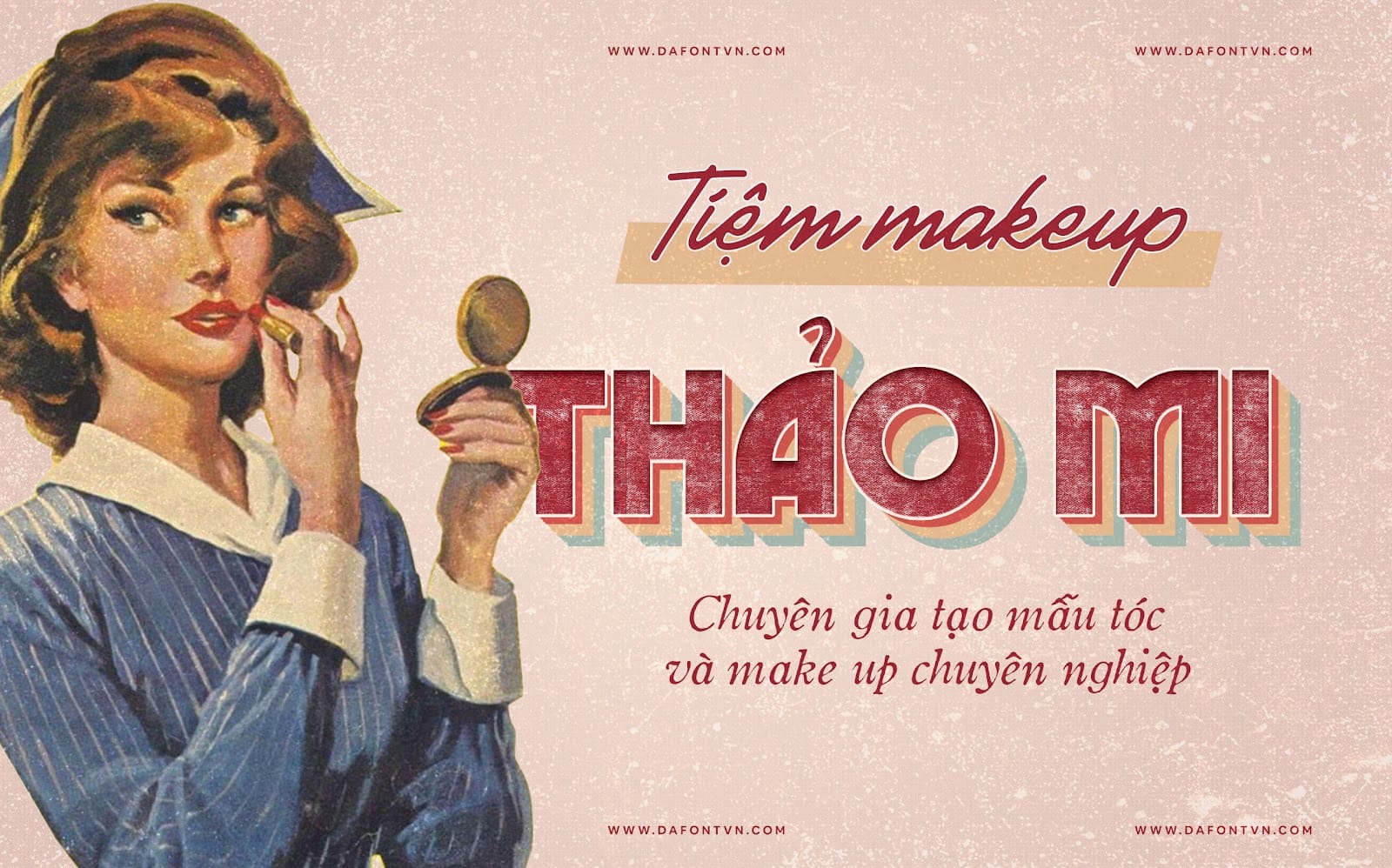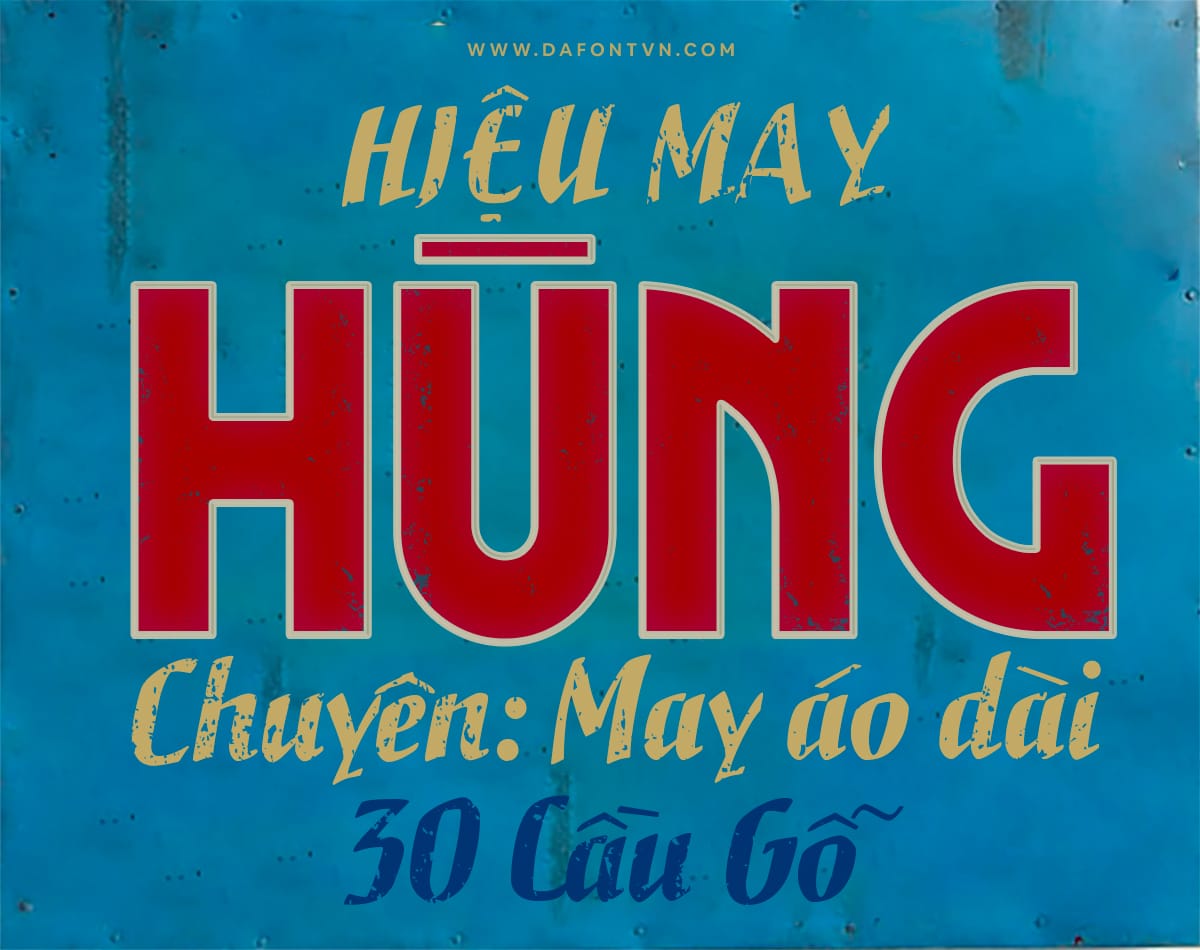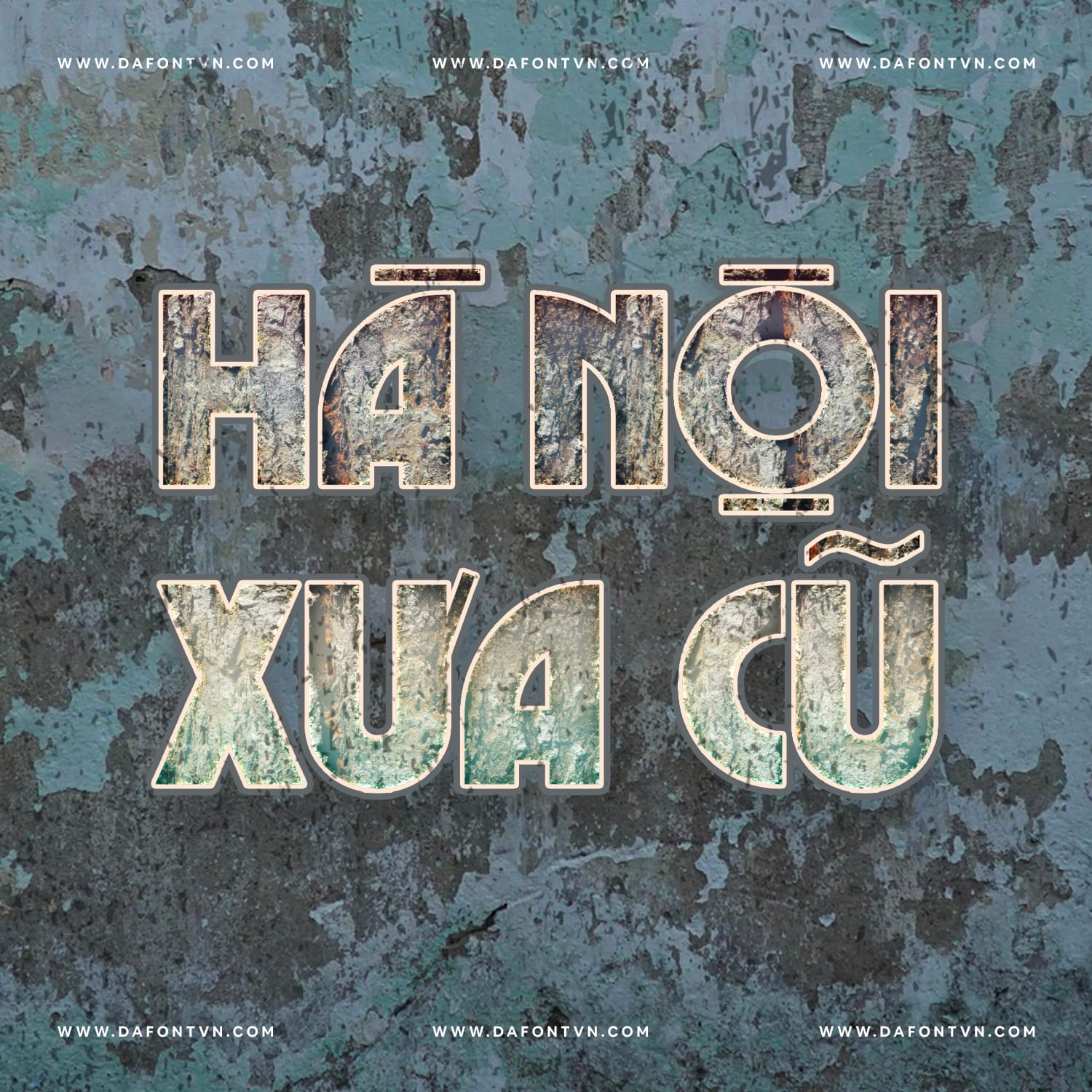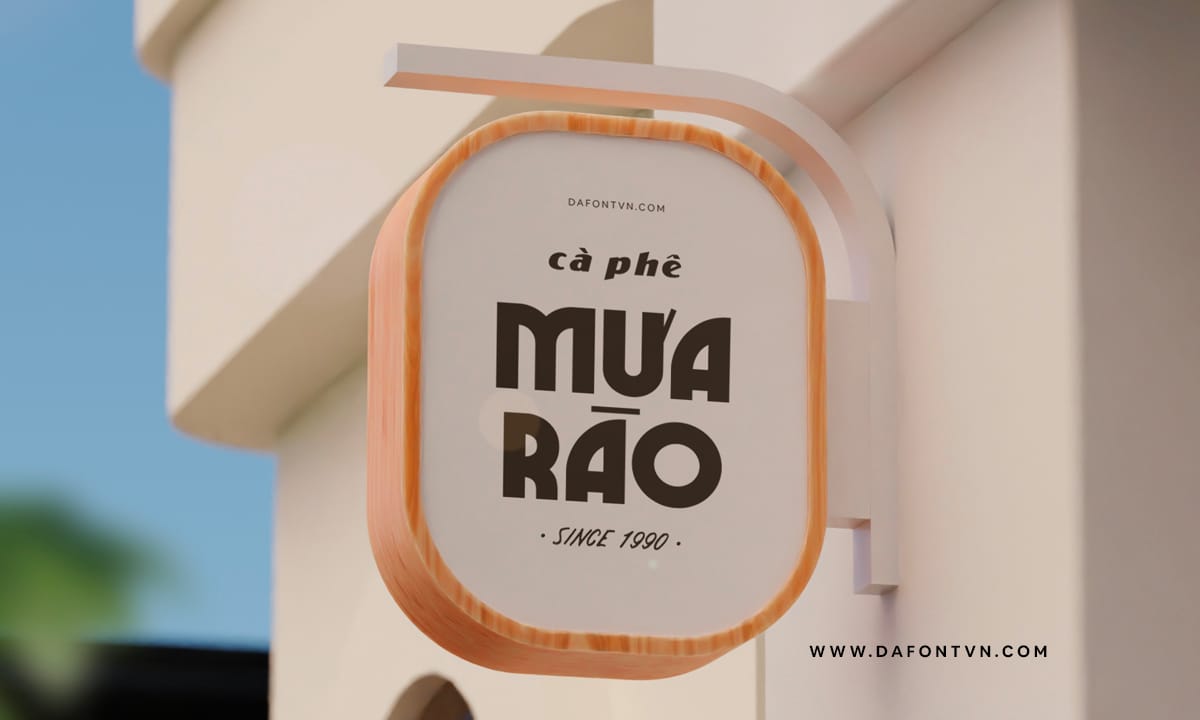
iCielBC Lodestone là một kiểu chữ sans serif ra đời vào năm 2017. Thiết kế ban đầu của nó có tên là “Marvin” và được tạo bởi Face Photosetting (London) vào đầu những năm 1970. Vì cái tên “Marvin” đã được một xưởng đúc khác sử dụng vào thời điểm xuất bản nên “Lodestone” đã ra đời.
Lodestone là một kiểu chữ cổ điển với các nét chữ được thiết kế dày, đậm. Font iCielBC Lodestone việt hóa với các nét dấu mang phong cách xưa cũ được lấy cảm hứng từ những biển hiệu xưa ở Việt Nam vào những thập niên 60-70.
iCielBC Lodestone mặc dù mang phong cách cổ điển nhưng nó vẫn được sử dụng tốt cho các thiết kế xưa cũ và hiện đại, bạn có thể sử dụng font này cho các thiết kế như: logo, xây dựng thương hiệu, tiêu đề, biển hiệu…